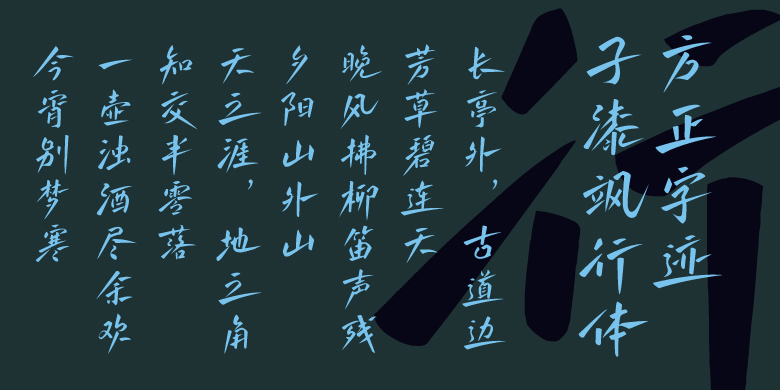
方正字迹-子漆飒行体
墨子漆
行楷、常规书写·毛笔
《方正字迹-子漆飒行体》是一款兼具传统行书气韵与现代设计张力的书法字体。字体以 “飒” 为精神内核,笔锋劲健爽利、结构灵动舒展,既有传统书法的骨力与气韵,又具备当代设计所需的力量感与辨识度。笔法:劲健爽利,主笔舒展、出锋利落,刚劲中藏灵动,尽显 “飒” 态; 结构:欹侧灵动,内紧外松,气脉贯通,打破刻板,自带动感韵律; 风格:传统为骨、现代为魂,辨识度拉满,利落大气,适配国潮审美; 价值:兼具书法文化底蕴与商业适配性,全场景可用,自带视觉张力。